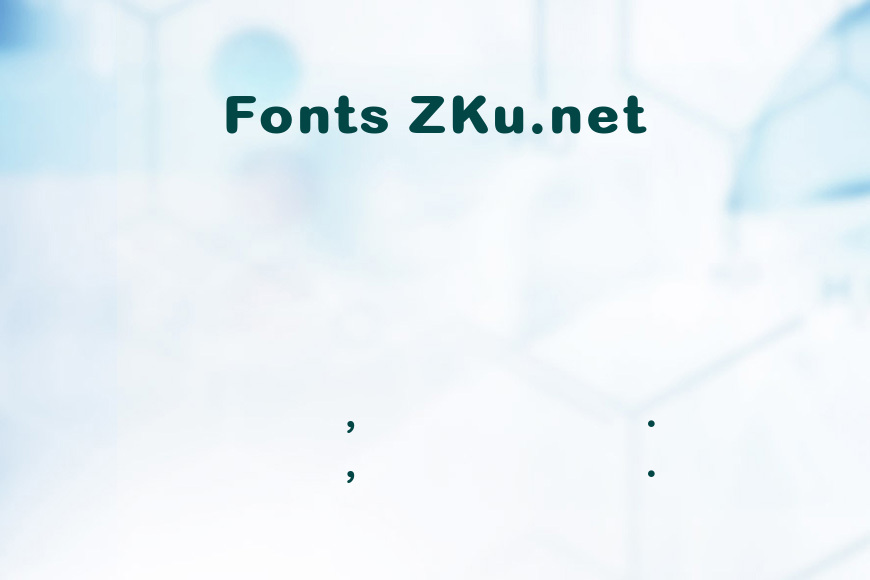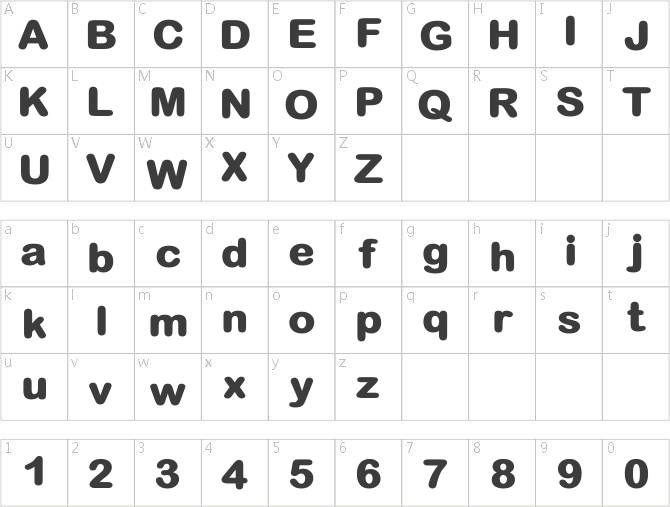
Arial Rounded MT Black 详情页
Arial Rounded MT Black
The font "Arial Rounded MT Black" is transferred from the font "Arial Rounded MT Bold" with numbers of scripts.